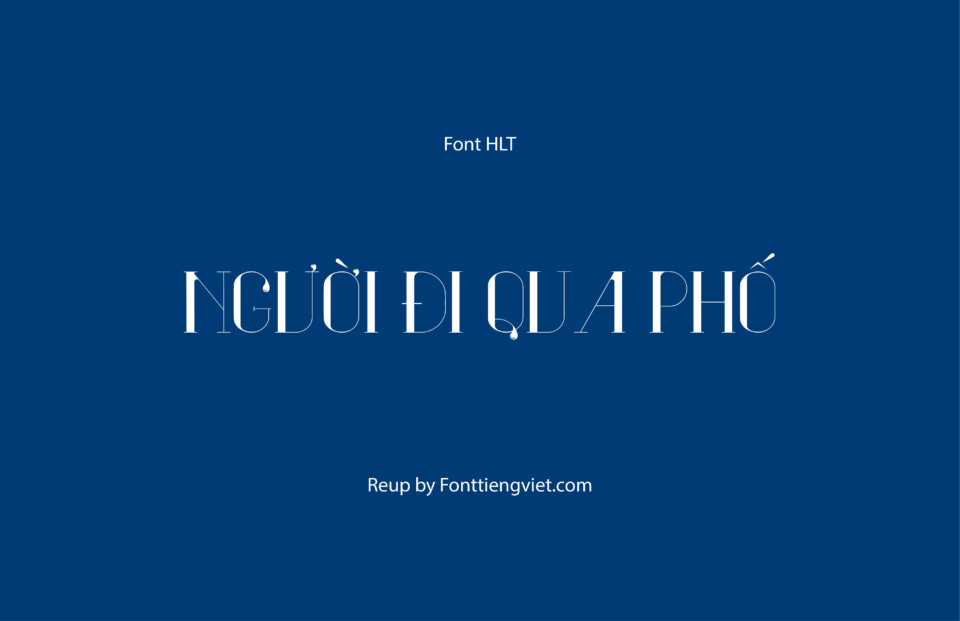
Font Việt hóa HLT Vindeco
Giới thiệu về bộ Font Việt hóa HLT Vindeco
Trong thế giới thiết kế đồ họa hiện đại, việc tìm kiếm một bộ Font Miễn Phí chất lượng và phù hợp với ngôn ngữ tiếng Việt là điều vô cùng quan trọng đối với các bạn học sinh và giáo viên. Font Việt hóa HLT Vindeco nổi lên như một sự lựa chọn hàng đầu nhờ phong cách Art Deco tinh tế và sang trọng. Đây là bộ phông chữ được đội ngũ HLT trau chuốt kỹ lưỡng về mặt hiển thị, đảm bảo không bị lỗi dấu khi sử dụng trong các phần mềm thiết kế hay văn bản hành chính.
Đặc điểm nổi bật của Font Việt hóa HLT Vindeco
Thiết kế cổ điển và ứng dụng linh hoạt
Font Việt hóa HLT Vindeco sở hữu những đường nét thanh mảnh nhưng vô cùng dứt khoát, mang đậm hơi thở của thập niên 20. Sự kết hợp giữa nét hình học và các góc bo tròn mềm mại giúp bộ font này trở nên cực kỳ linh hoạt. Bạn có thể sử dụng nó để làm tiêu đề cho các bài thuyết trình, thiết kế bìa báo tường, hay trang trí các ấn phẩm kỷ yếu nhà trường. Khả năng hiển thị sắc nét giúp người xem dễ dàng tiếp nhận thông tin một cách chuyên nghiệp nhất.
Kết luận về bộ phông chữ HLT Vindeco